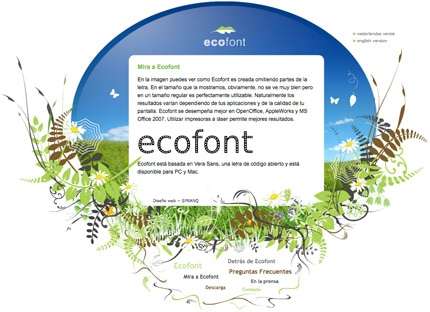
Pues puede sonar raro, pero si empezamos a razonar es cierto que en el proceso diario de impresión (tÃpico documento que en dos dÃas marchará a la papelera), se gasta mucha cantidad de tinta, perjudicial para el medio ambiente y también para nuestros bolsillos. Esto fue lo que pensaron desde el estudio creativo SPRANQ y como obtener una fuente que ahorrara tinta a la hora de imprimir documentos.
Después de muchas pruebas la solución llegó en forma de «queso gruyere», es decir, agujerar las diferentes letras para que al imprimir los agujeros queden en blanco y por lo tanto sin rellenar de tinta. Está claro que no «se ve bonito» pero es totalmente legible y según las pruebas ahorra un 20% de tinta respecto de otras fuentes clásicas como la Times. Puede parecer cuestión menor, pero imaginemos lo que ahorraremos a final de año tanto en tinta como en dinero. Ecofont es totalmente gratuita y la podemos descargar en formato .ttf.